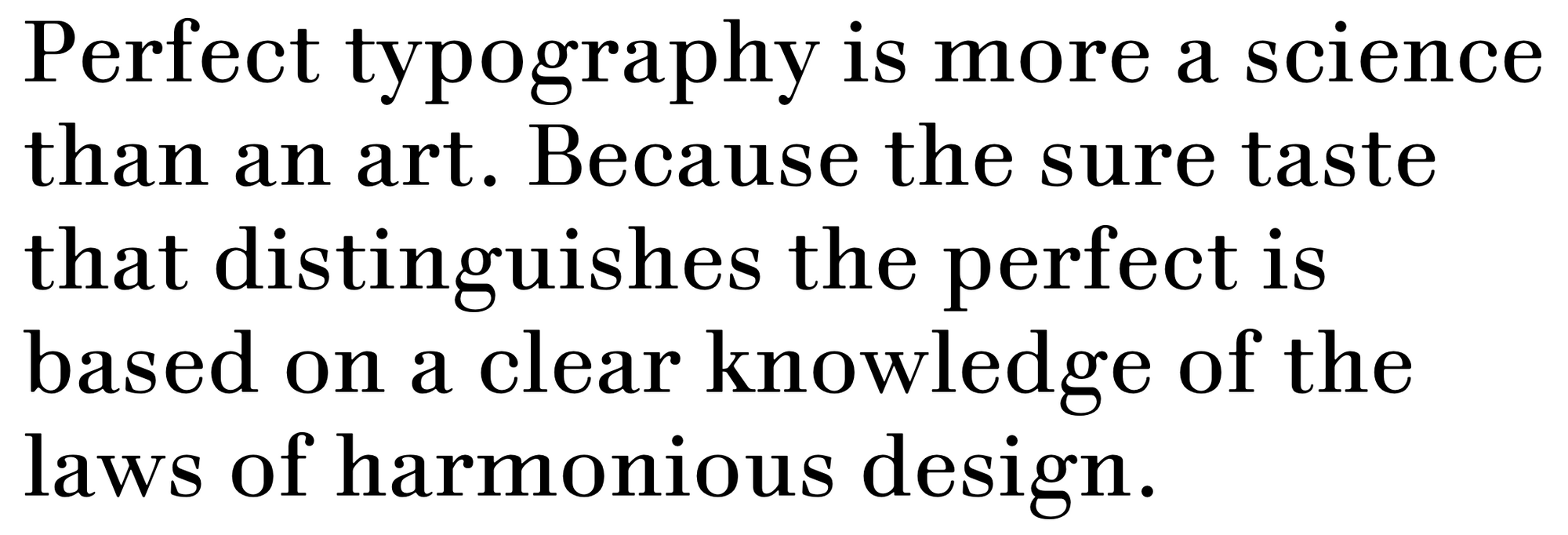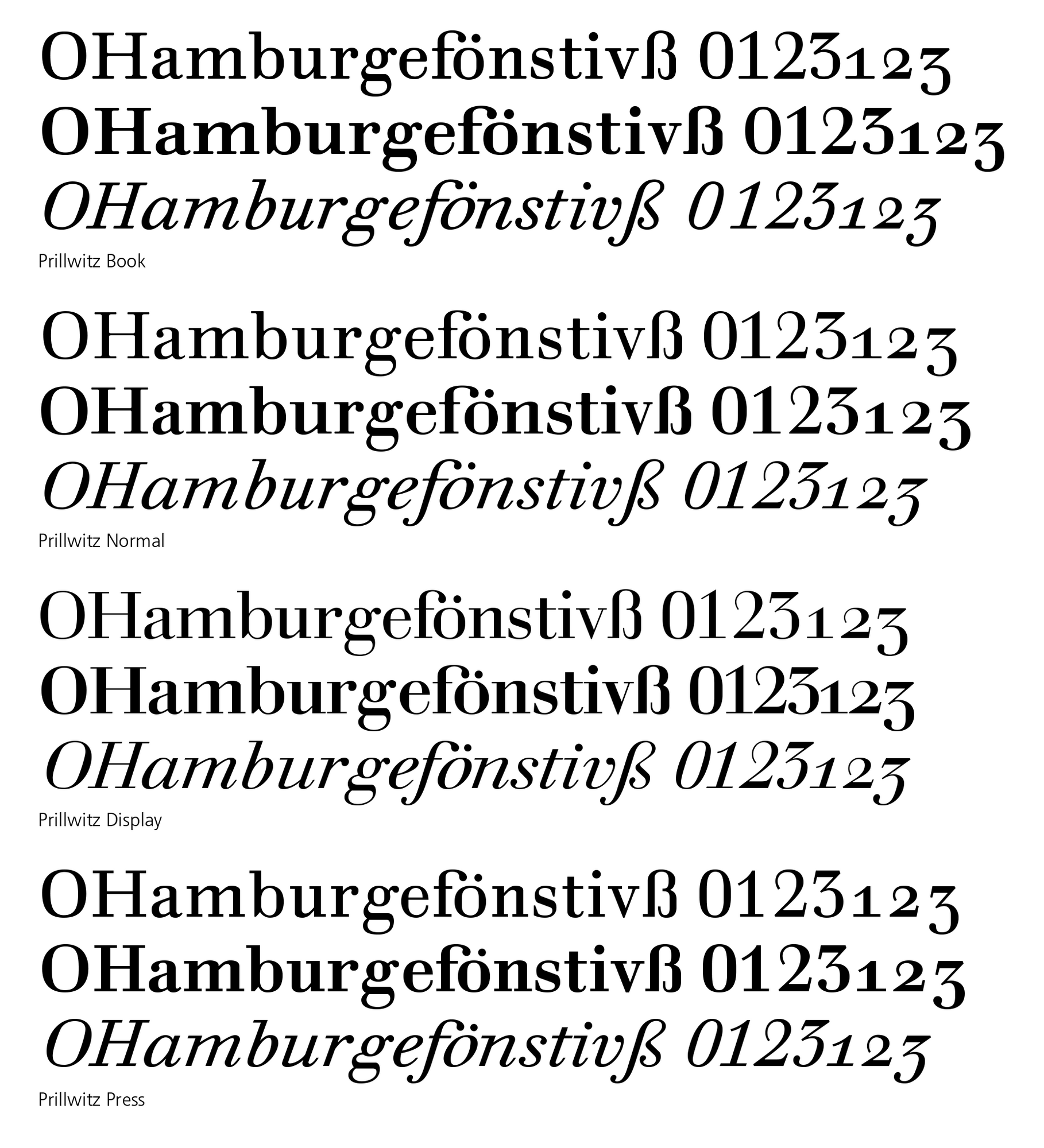
- 2005
- Antiqua statisch
- Versaleszett:
- enthalten
Der Jenaer Schriftgießer Johann Carl Ludwig Prillwitz war Ende des 18. Jahrhunderts mit seinen Schnitten der »Didotschen Lettern« erfolgreich. Eine umfassende Neuinterpretation, ausgehend von den Prillwitz-Originalmustern, nahm Ingo Preuß Anfang des 21. Jahrhunderts vor. Seine Prillwitz wurde in drei optischen Größen (Book, Regular und Display) angelegt. Der als NP (NewsPrint) bezeichnete Schnitt ist speziell für einen Druck in kleinen Größen auf Zeitungspapier geschaffen und wurde aus der Display entwickelt. Für die Regular – und stärker noch die Book – wurde eine weiche und sehr lesefreundliche Outline durch eine s. g. Verschmitzung erreicht und in zahlreichen Testdrucken optimiert. Die Scharfkantigkeit und der übliche maximale Strichstärkenkontrast bekannter klassizistischer Schriften (Didot, Bodoni) wurde durch das Studium der originalen Drucke zugunsten einer sehr guten Lesbarkeit auch in kleinen Schriftgraden überarbeitet.
Die Schrift-Familie enthält alle wichtigen Zeichen für effizientes und typographisch hochwertiges Arbeiten: Kapitälchen mit entsprechenden Ziffern in Kapitälchenhöhe (tabellarisch und proportional), Minuskel- und Mediävalziffern (tabellarisch und proportional), Bruchziffern und einen kompletten Akzentsatz für alle lateinischen Schriften.